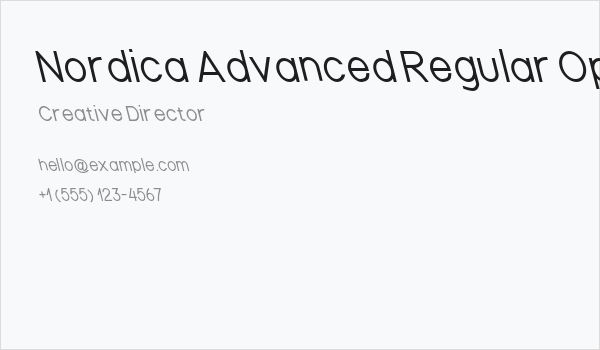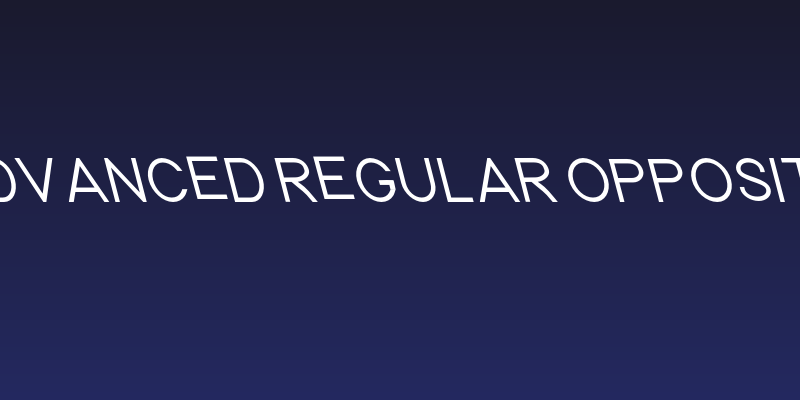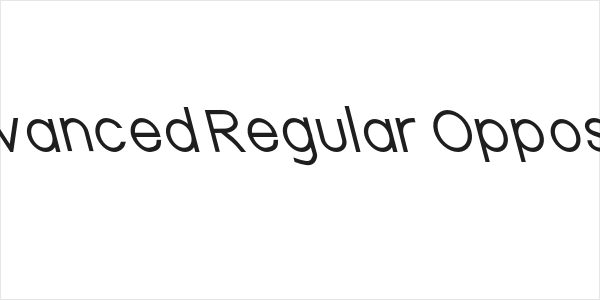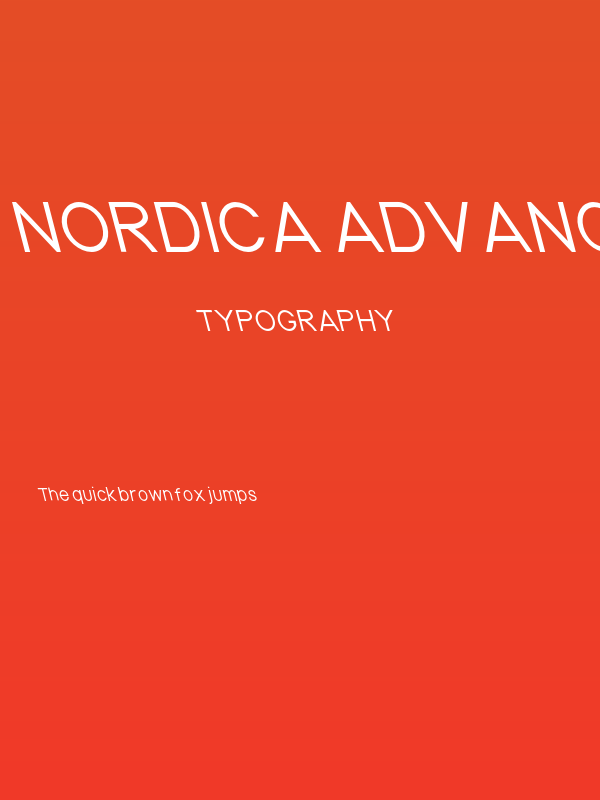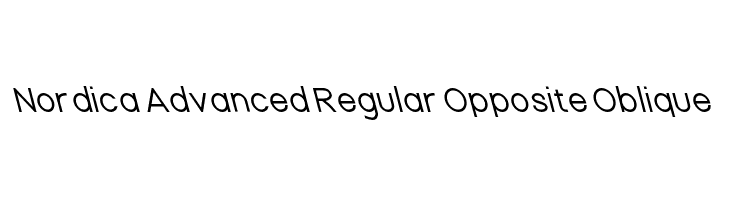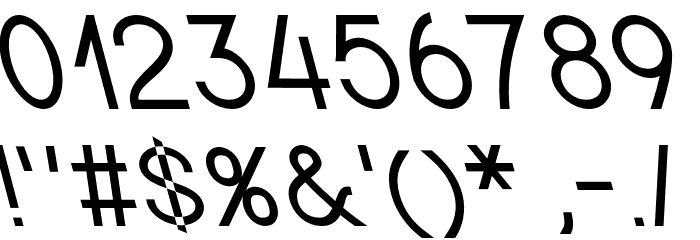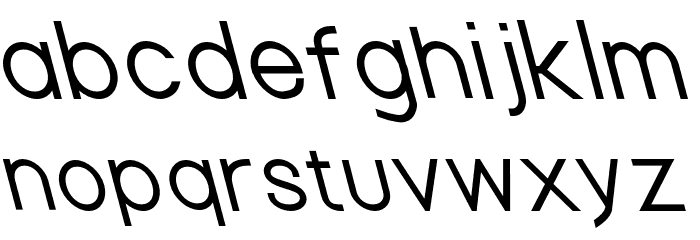
Nordica Advanced Regular Opposite Oblique Font
| Projets proposés | Ideal for branding, advertising, digital interfaces, and editorial design where a modern and professional look is desired. |